Font Việt Hóa là gì? Font Việt Hóa có từ khi nào?
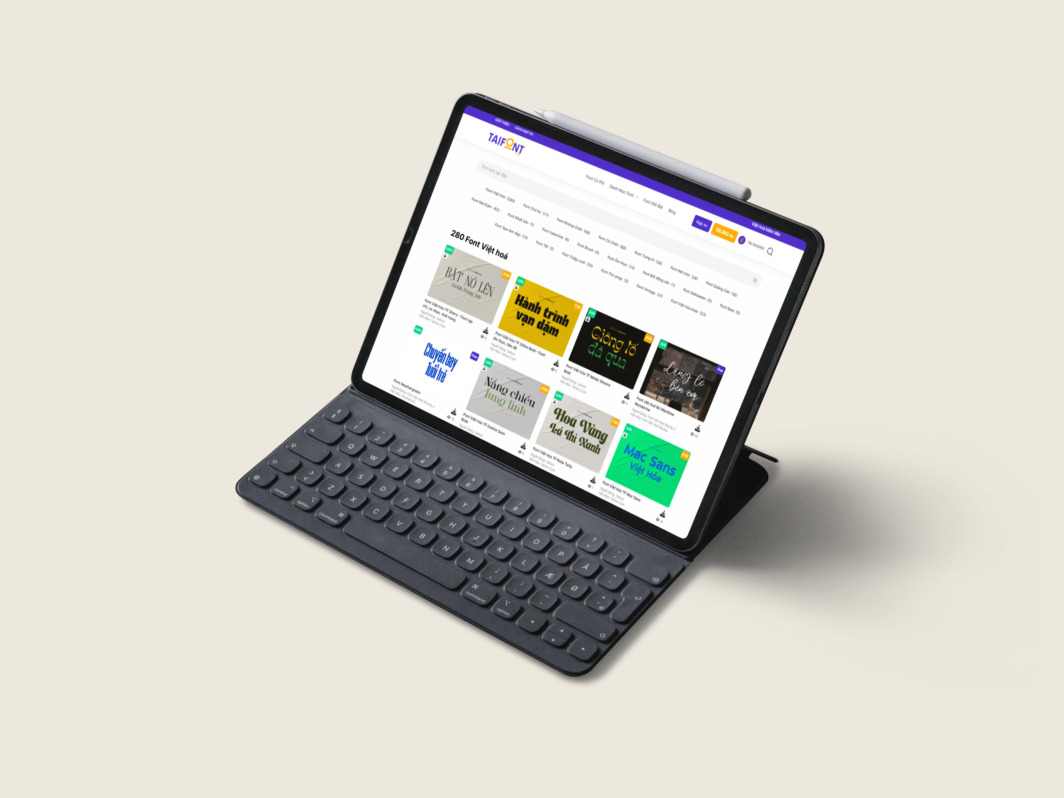
Font Việt Hóa là gì?
Font Việt hóa là các kiểu chữ (font) đã được điều chỉnh hoặc mở rộng để hỗ trợ đầy đủ bộ ký tự tiếng Việt, bao gồm các dấu thanh và chữ cái đặc biệt như “ă, â, đ, ê, ô, ơ, ư”. Quá trình Việt hóa một font thường bao gồm việc thêm các dấu tiếng Việt vào bộ ký tự gốc, điều chỉnh khoảng cách giữa các ký tự để đảm bảo tính thẩm mỹ và khả năng đọc tốt.
Font Việt Hóa có từ khi nào?
Việt hóa font bắt đầu xuất hiện phổ biến từ những năm 1990 khi máy tính cá nhân và phần mềm xử lý văn bản trở nên phổ biến ở Việt Nam. Một số cột mốc quan trọng:
- Trước năm 1990: Chủ yếu sử dụng font dựa trên bảng mã ASCII hoặc font tùy chỉnh để đánh tiếng Việt trên máy đánh chữ hoặc máy tính đời đầu.
- Những năm 1990: Font chữ đầu tiên được Việt hóa xuất hiện, nhưng còn hạn chế do hệ thống mã hóa phức tạp như TCVN3, VNI.
- Những năm 2000: Bộ mã Unicode trở nên phổ biến, thúc đẩy việc Việt hóa font dễ dàng hơn. Nhiều nhóm thiết kế và cá nhân bắt đầu Việt hóa các font quốc tế.
- Hiện nay: Hầu hết các font chuyên nghiệp đều có sẵn phiên bản hỗ trợ tiếng Việt, và nhiều designer Việt đã tự tạo font hoàn chỉnh dành riêng cho tiếng Việt.